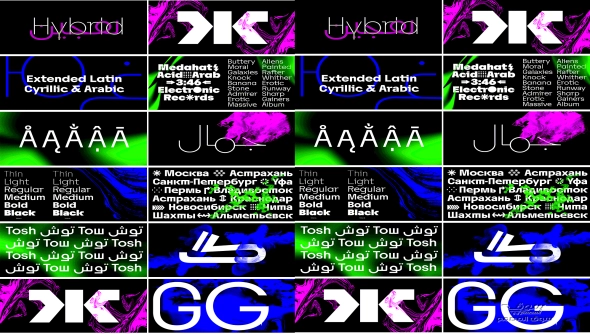
توش هو تهجين بين الأشكال الميكانيكية الهندسية والروح العضوية. يتم التعبير عن الحمض النووي الفريد والمعاصر بشكل حازم بأسلوب sans-serif ويتكون من عائلتين من محرفين مزدوجين: Tosh A و Tosh B. كلاهما يعبر عن نفسه بلغة مشتركة ولكن لهما خصائصه الخاصة. Tosh A هو الأكثر هندسية بين المتغيرين ، بينما Tosh B هو الأكثر إنشاءًا. قوتهم المشتركة هي اللعب بمزيج من الأشكال لخلق إيقاع قراءة نابض بالحياة.
Tosh Font Family